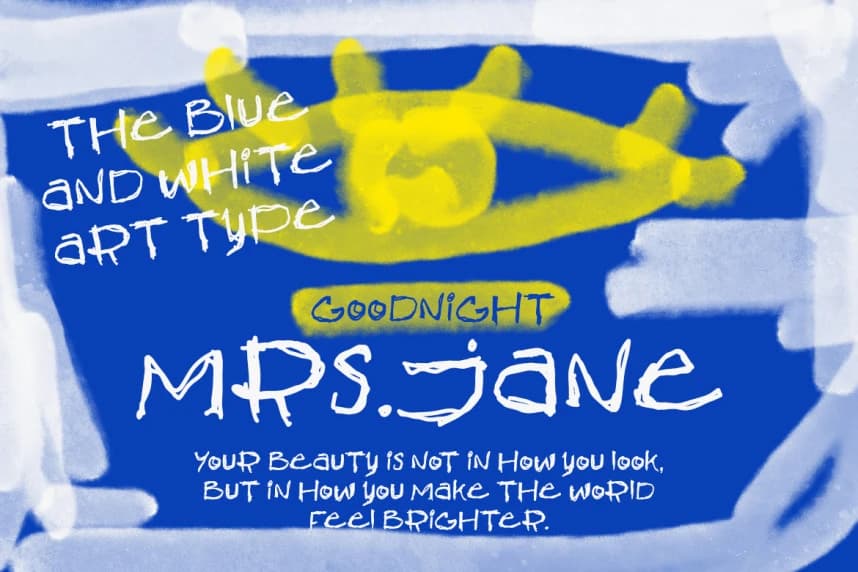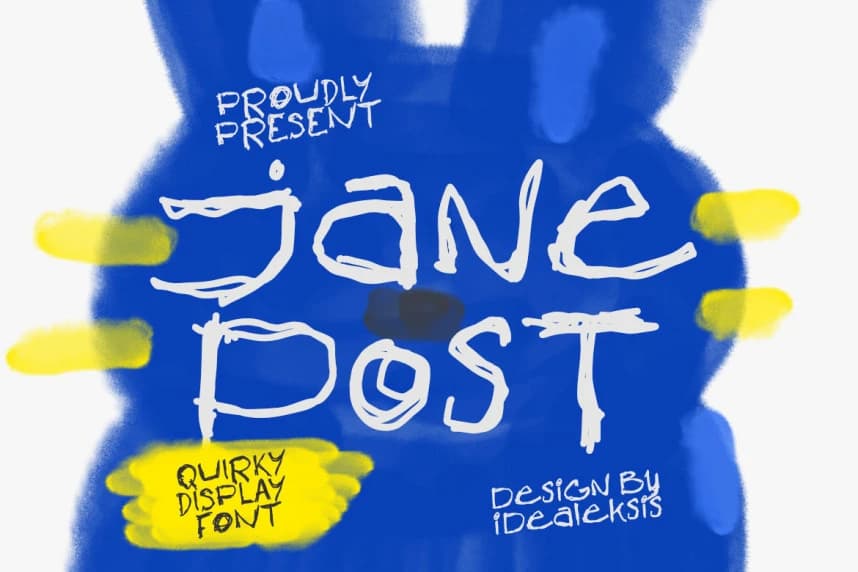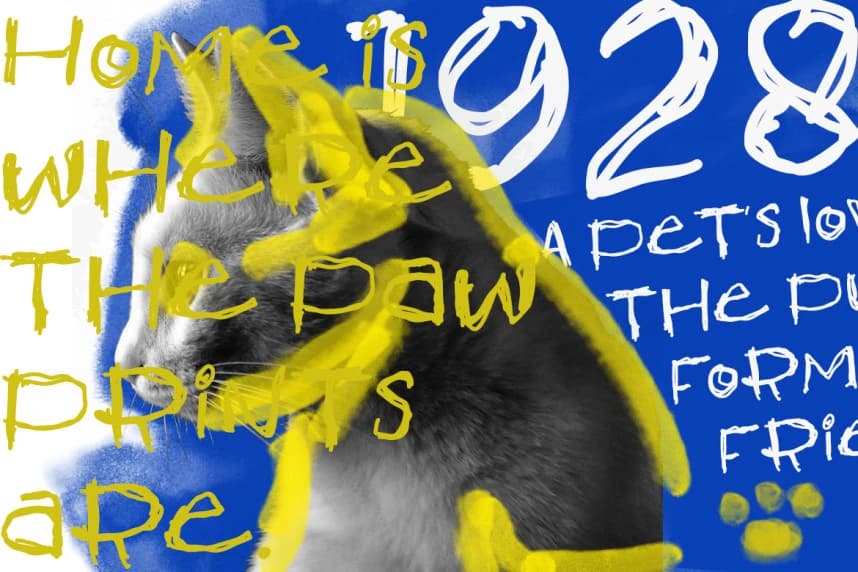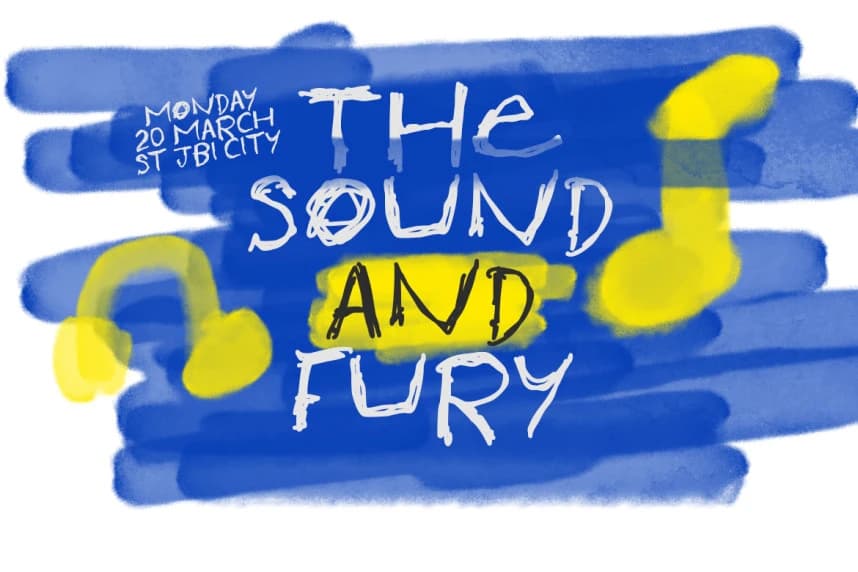
Jane Post – Quirky Display Font - Bu gösteri yazı tipi, düzensiz, titrek çizgiler ve tutarsız harf biçimleriyle karakterize edilen ham, elle çizilmiş bir estetiğe sahiptir. Glifler, ağırlık ve taban hattı hizalamasında oyunbaz bir uyumsuzluk sergileyerek ona spontane ve enerjik bir hava verir.
Jane Post – Quirky Display Font - Bu gösterim yazı tipi, düzensiz, sarsak çizgiler ve tutarsız harf biçimleriyle karakterize edilen ham, elle çizilmiş bir estetiğe sahiptir. Glifler, ağırlık ve taban çizgisi hizalamasında oyunbaz bir düzensizlik sergiliyor; bu da ona kendiliğinden gelen ve enerjik bir his veriyor.